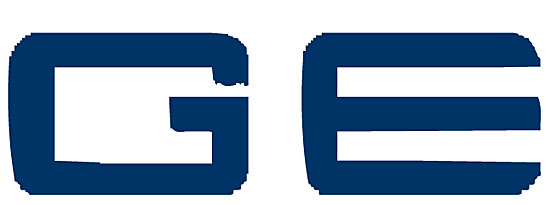
kann mir jemand die Schrift in dem Logo auf http://www.gemclass.com nennen? Ich suche diese schon sehr lange, konnte aber nur ähnliche finden. Das ist die selbe, die auch im RTL Explosiv-Logo genutzt wird!
kann mir nicht vorstellen das dies ein font ist.
sieht »handgemacht« aus. der gleiche font wie
bei rtl-explosiv ist es auch nicht, sofern du den
von der webseite meinst (anhang).
Ah sorry, hab nicht gesehen, dass sie das Logo bei RTL erneuert haben, das Alte war die Schrift. Die Konturen habe ich schon öfter gesehen, ich bin mir sicher, dass es eine (vielleicht nur ähnliche) Schrift gibt. Würde mich sehr freuen, wenn diese jemand kennt!
Habe noch mal genau geschaut und muss mich entschuldigen: Das exclusiv (und nicht explosiv) Logo sieht ähnlich aus. Dies scheint ein Font in zwei Schnitten zu sein. Ich hoffe es zumindest...
Keiner sonst eine Idee? Würde mich sehr freuen, wenn die Schrift jemand kennt...
wenigstens ein ähnlicher würde mir helfen...
machts euch doch nicht immer so leicht. ähnlich ist nicht gleich.
ff gothic one one nehmen, hier und da etwas dranbauen – fertig.
dann hast du was individuelles auf basis eines richten fonts.
ansonsten schau dir die trademarker light an, oder register von device, schau bei t26.com die haben da eine menge ...
oder zahl xx euro und frag fontshop, die empfehlen die auch gern welche
Vielleicht bin ich ja friseur und möcht ein logo haben *g* Ne, im ernst, hast recht, sie sieht doch nicht so unähnlich aus... Vielen Dank für Deine Tipps, werd ich mal reinschauen!